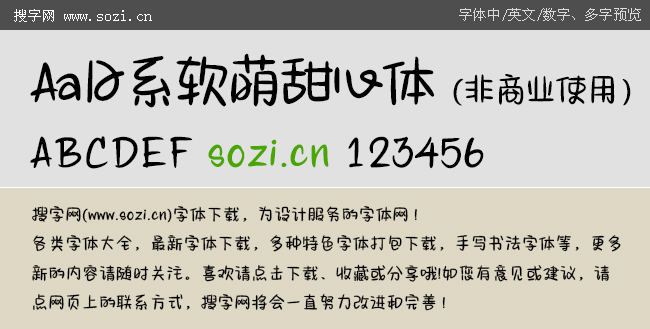
Aa日系軟萌甜心體
搜字網(wǎng)給大家提供一款A(yù)a日系軟萌甜心體(非商業(yè)使用)中文字體下載,Aa日系軟萌甜心體是一款卡通藝術(shù)字體,字形可愛俏皮,透出一些稚氣。書寫上融入的連筆的寫法有幾分日語中平假名的意味,活潑靈動(dòng)。適合應(yīng)用于藝術(shù)設(shè)計(jì)、平面宣傳設(shè)計(jì)、網(wǎng)頁設(shè)計(jì)、海報(bào)設(shè)計(jì)等應(yīng)用(此字體為個(gè)人非商用版,商用可以聯(lián)系QQ:1006760504)。